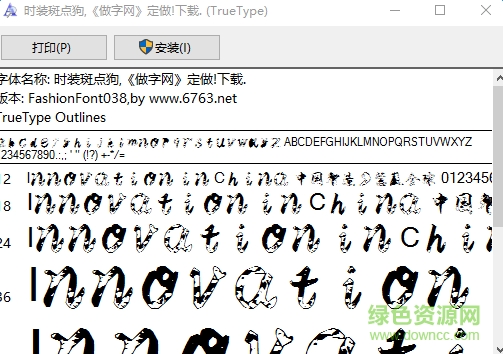
時(shí)裝斑點(diǎn)狗體是一款很有個(gè)性的電腦藝術(shù)字體,這款字體寫出來的字不像普通字體那樣呆板,它很有自己的特色,字形上斑斑點(diǎn)點(diǎn)的很是可愛,喜歡的朋友可以來綠色資源網(wǎng)下載。
時(shí)裝斑點(diǎn)狗體是真的很不錯(cuò)的,特別適用于藝術(shù)方面,不管是廣告設(shè)計(jì)、還是在書畫上面題字題詞都是可以的,歡迎大家來綠色資源網(wǎng)下載。